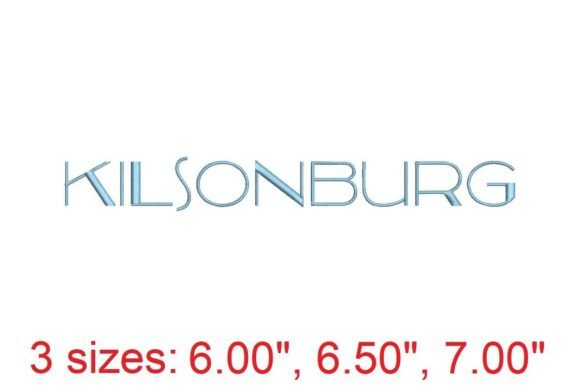
Kilsonburg Embroidery Font
適切なデザイン要素を見つけるのは難しい場合がありますが、Kilsonburg Embroidery Fontは作品を即座に引き立てる優れたコレクションを提供します。
POD(オンデマンド印刷)製品、結婚式の招待状、またはソーシャルメディアのグラフィックを作成している場合でも、Kilsonburg Embroidery Fontは理想的です。